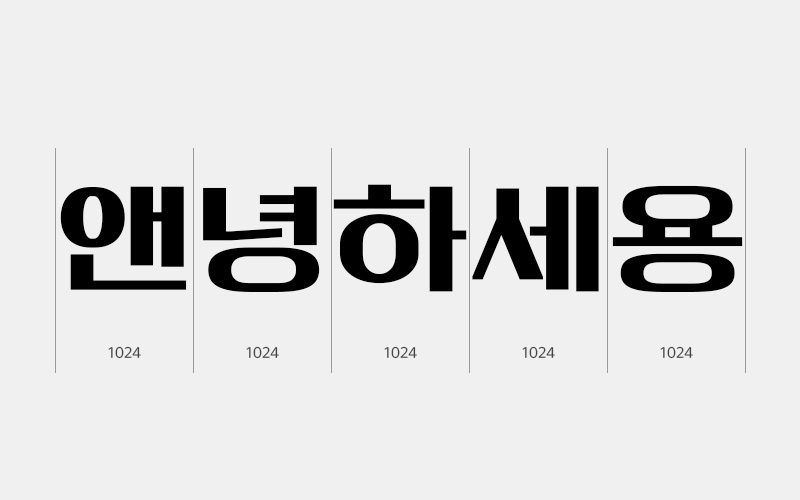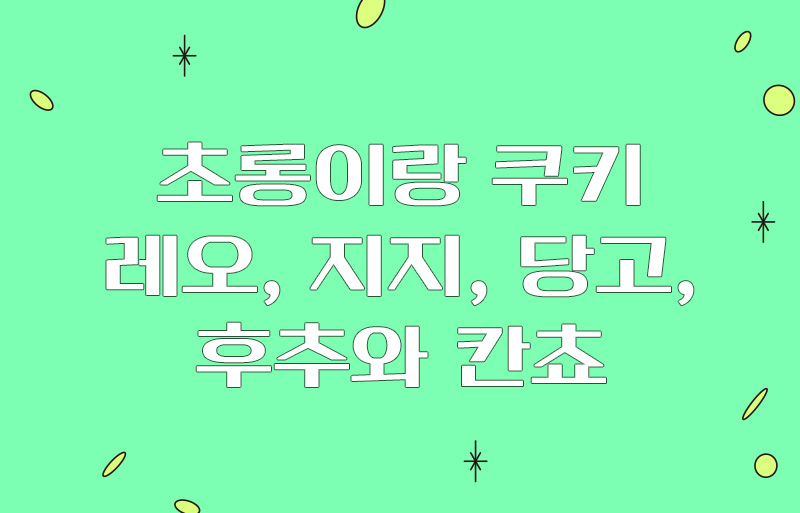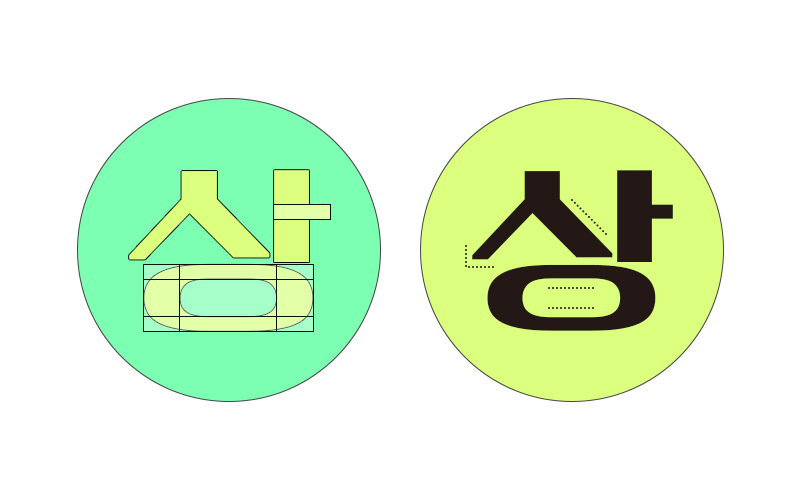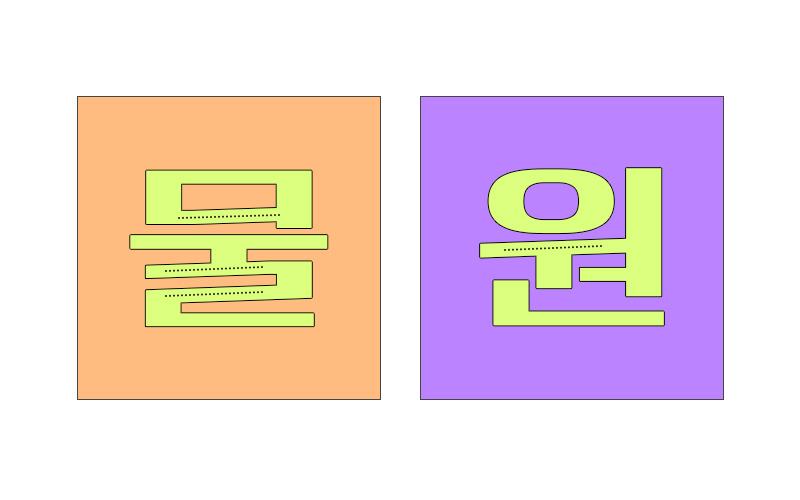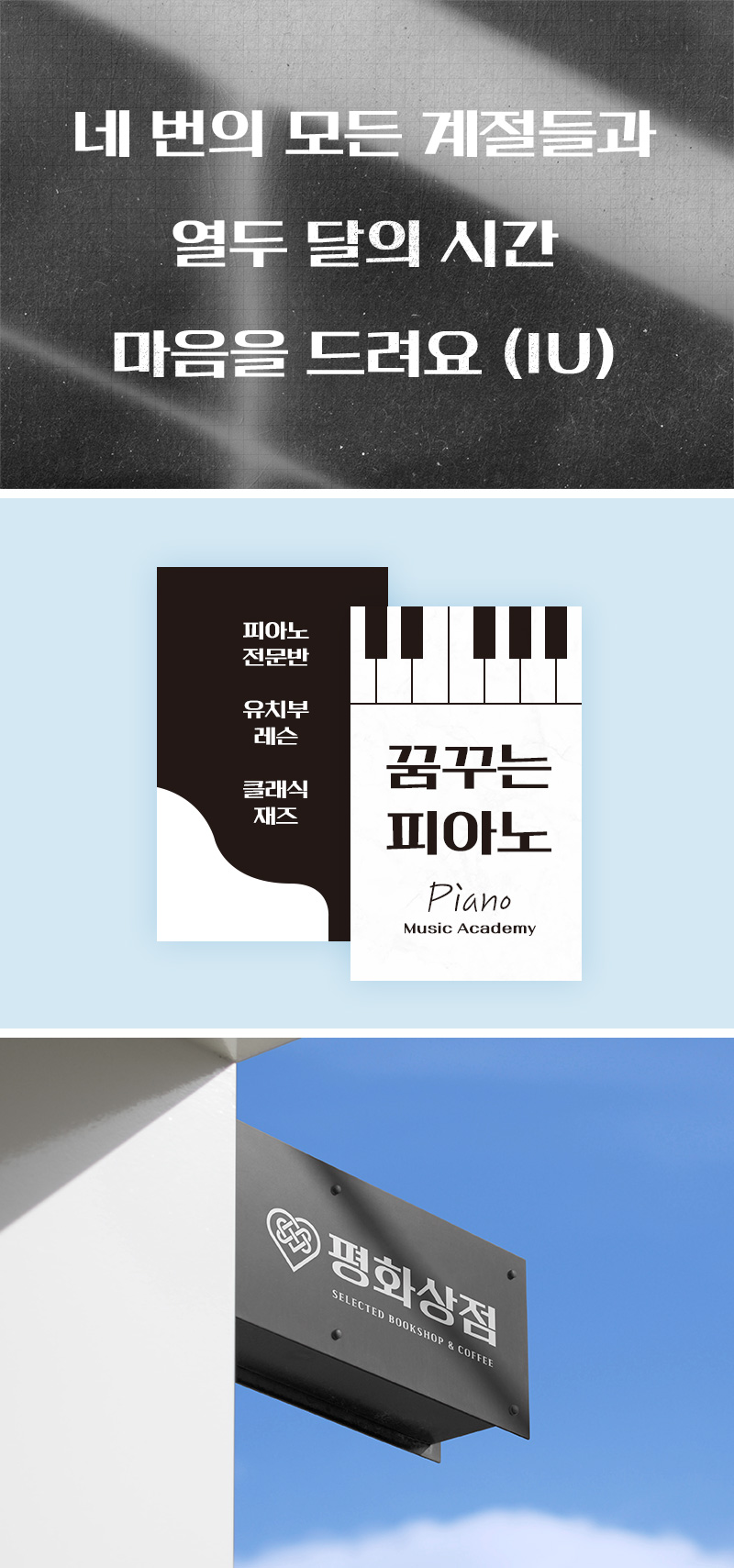
RixMarkerpen
1 Style - 5mm두꺼운 마카펜으로 쓴 글씨에서 영감을 얻어 제작된 시원한 인상의 글꼴입니다.
넓고 여유로운 자폭과 납작한 펜으로 쓴 듯한 강한 획의 대비가 특징입니다.
높은 주목도가 필요한 콘텐츠에 타이틀이나 부제목 서체로 모두 활용할 수 있습니다.
| FontFamily | Rix마카펜 / RixMarkerpen |
| Design | Yu Hyun-Ju |
| Direction | Park Yong-rak |